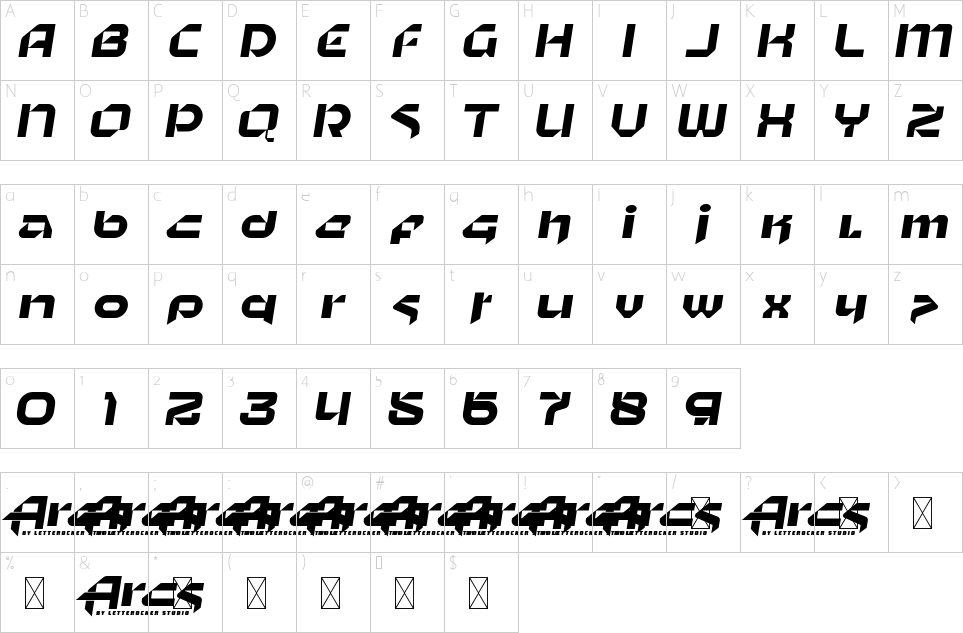
Descubra a elegância e a versatilidade da Arcs Font, uma fonte gráfica gratuita disponível tanto para Windows quanto para Mac. Lançada pelo Studio Lettercorner, Arcs oferece um estilo fluido e contínuo, perfeito para estilos modernos e futuristas. Se você busca uma fonte única e criativa, que combina elegância com modernidade, Arcs é uma escolha atraente. Através dela, sua próxima criação pode ter um aspecto que destacará sua personalidade e estilo. Com sua simplicidade e beleza, Arcs é uma fonte ideal para qualquer projeto de design. Desde gráficos de publicidade até design de interfaces de aplicativos, a Arcs não deixa nada a desejar. Aproveite a Arcs Font agora, e veja como ela pode transformar seu design.